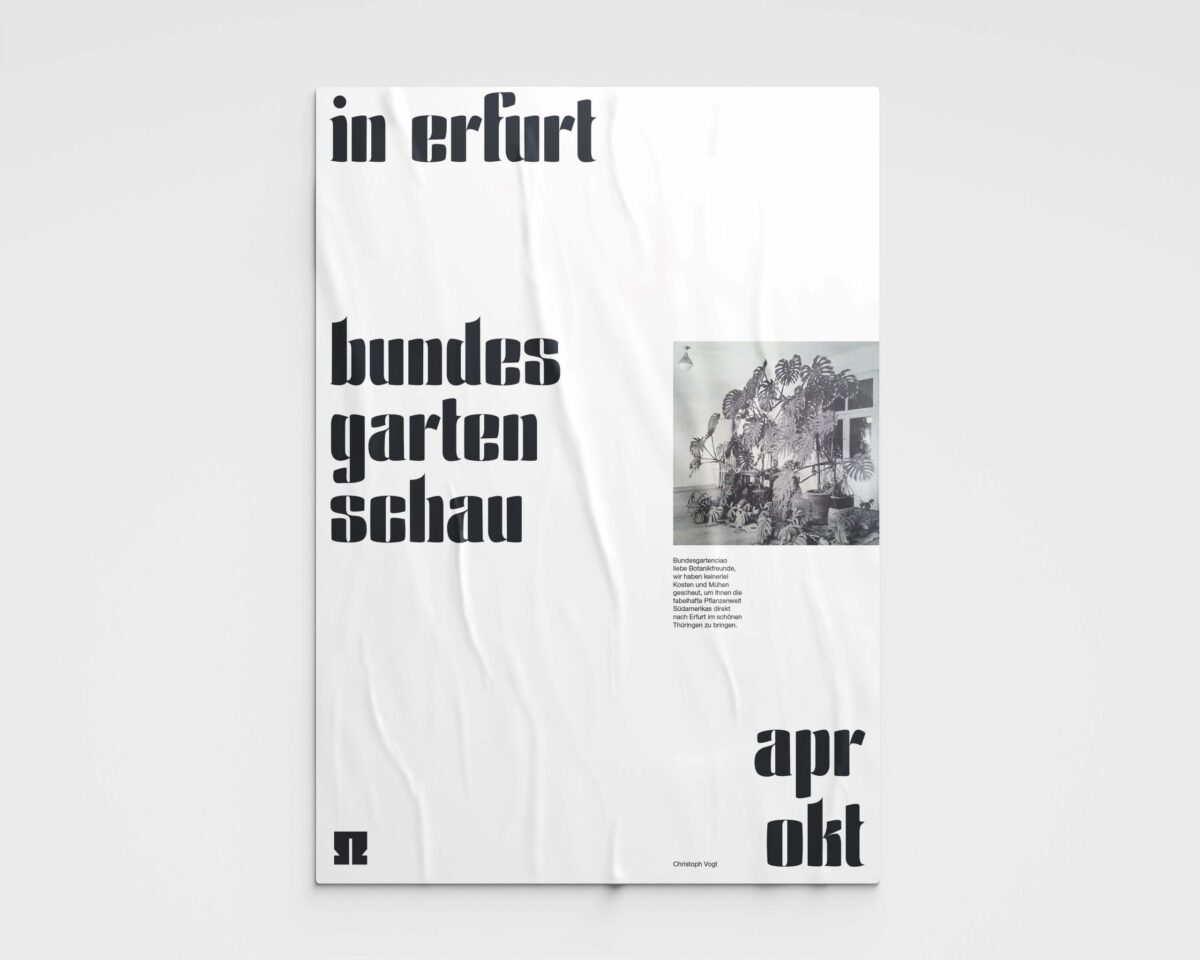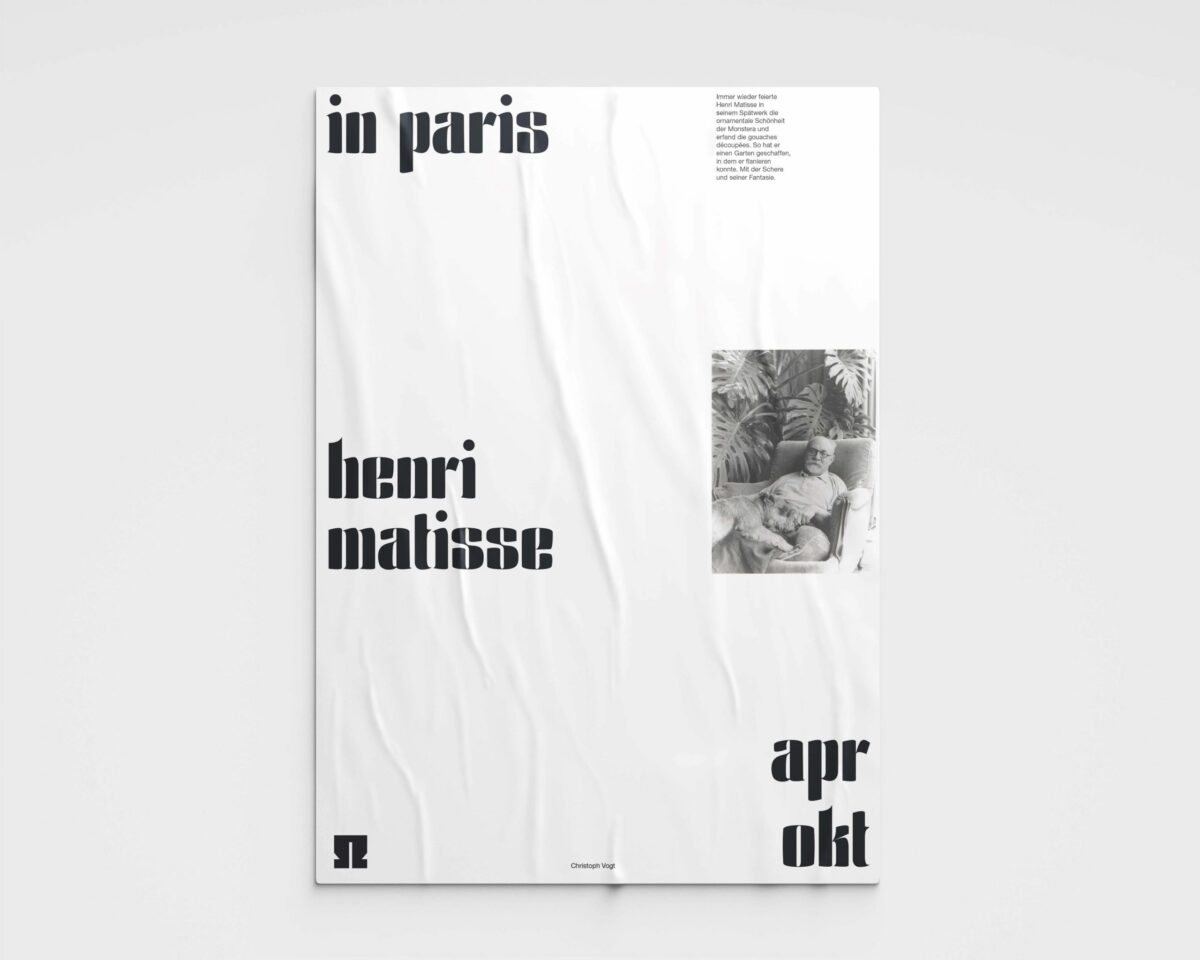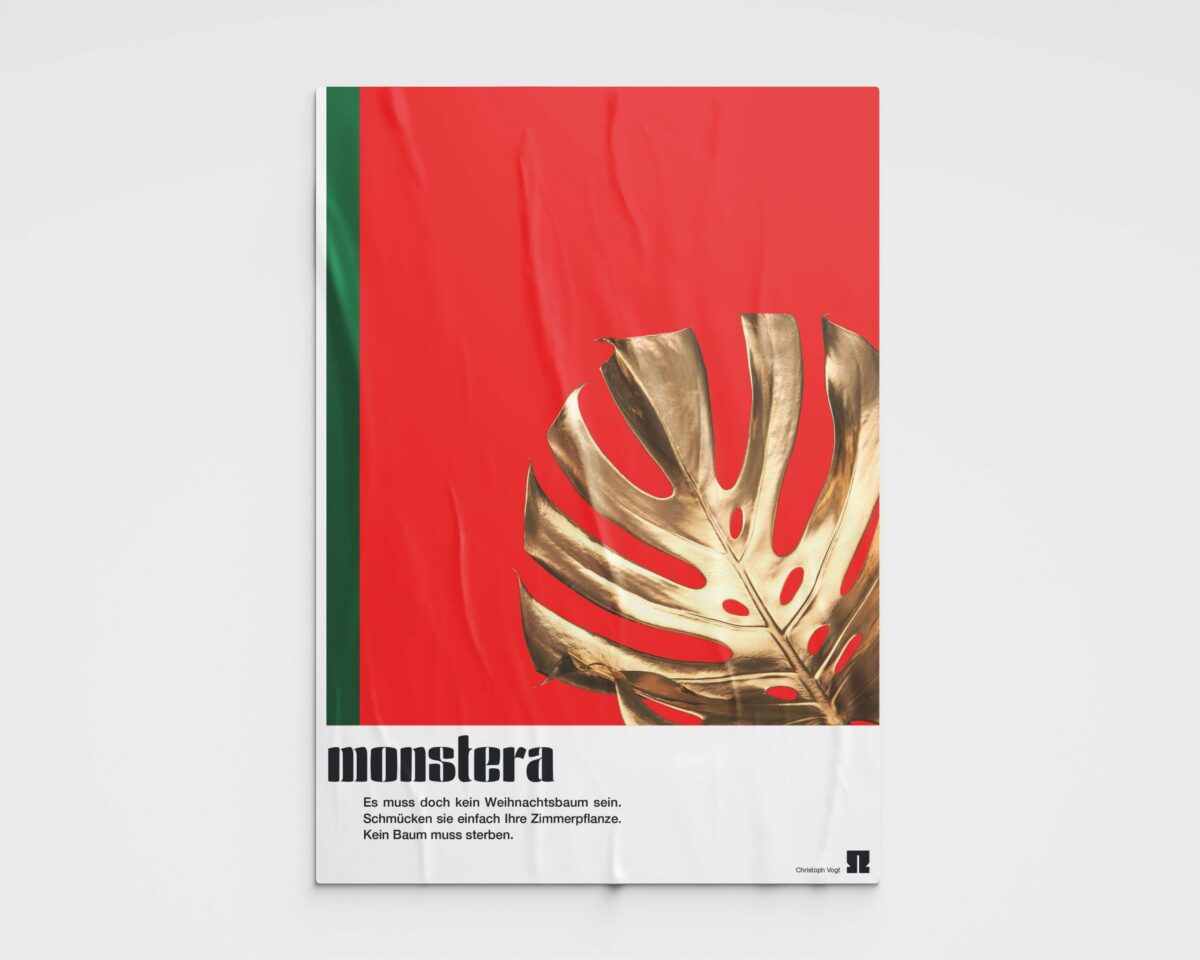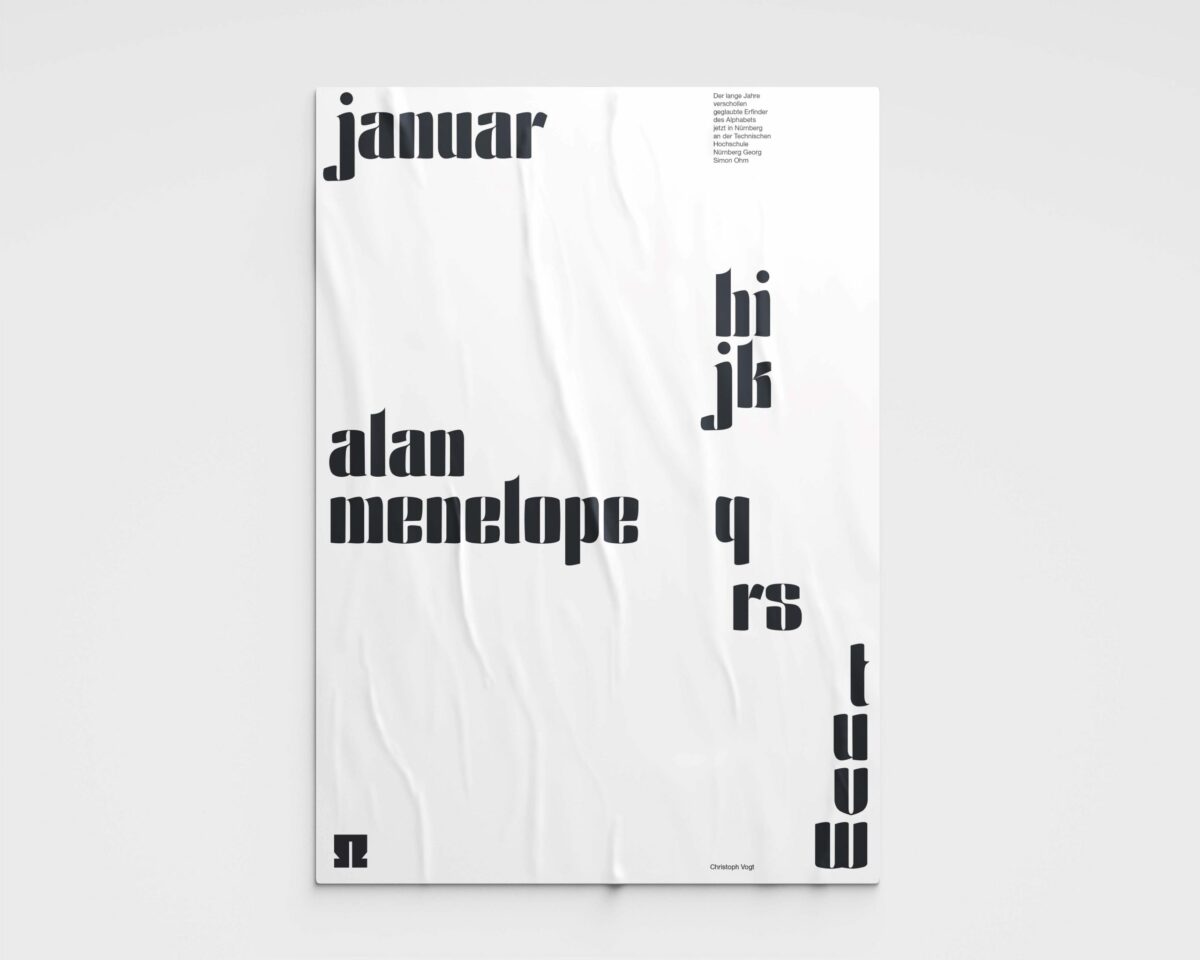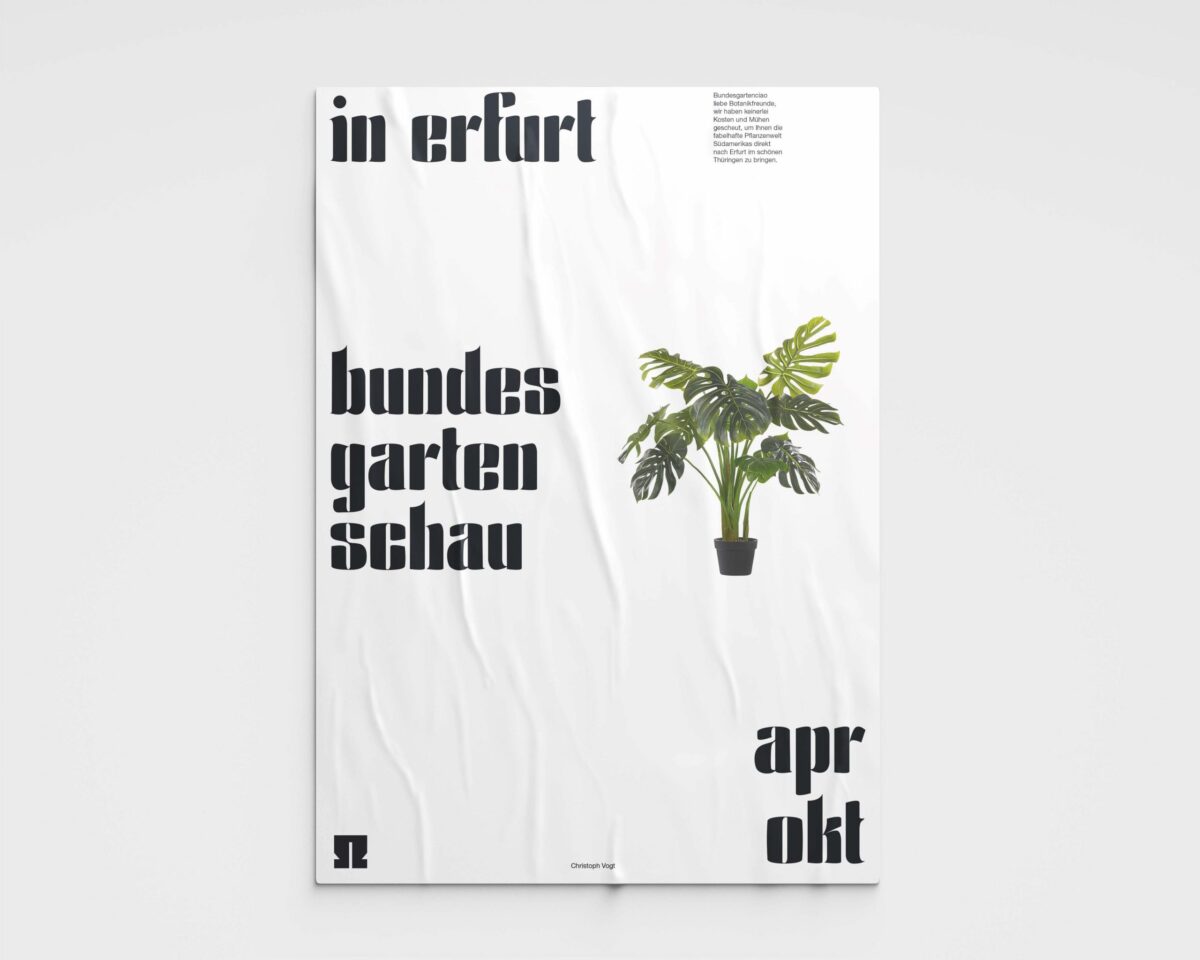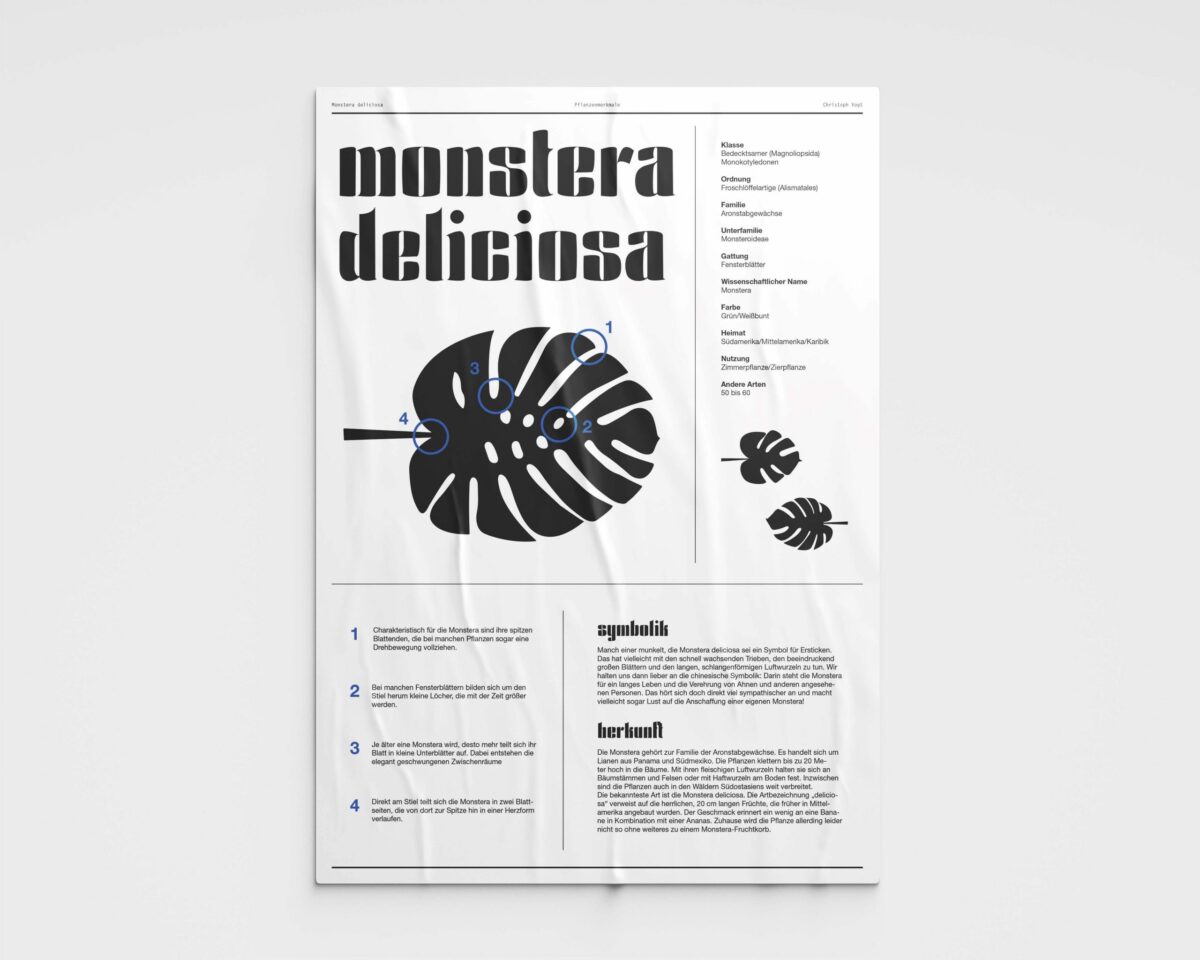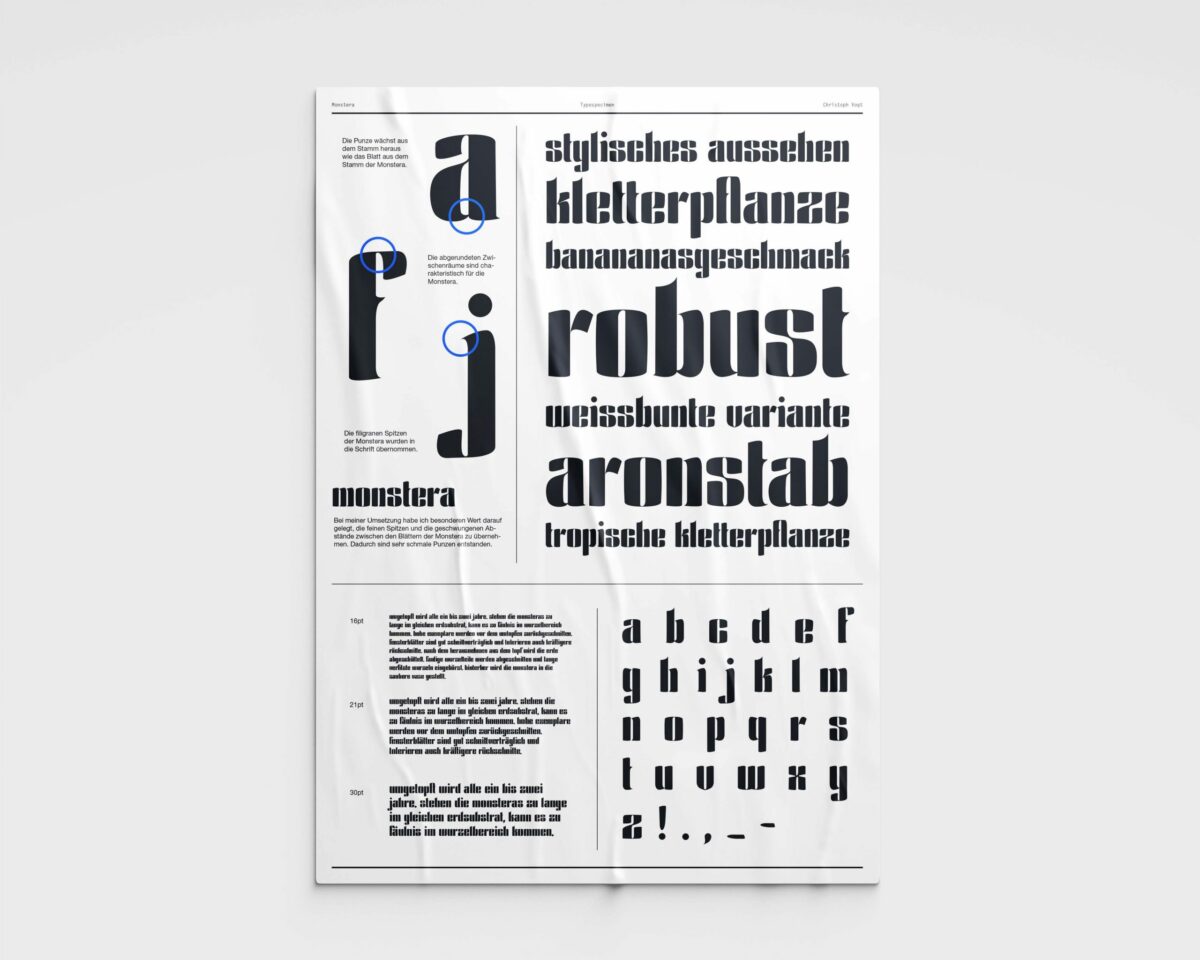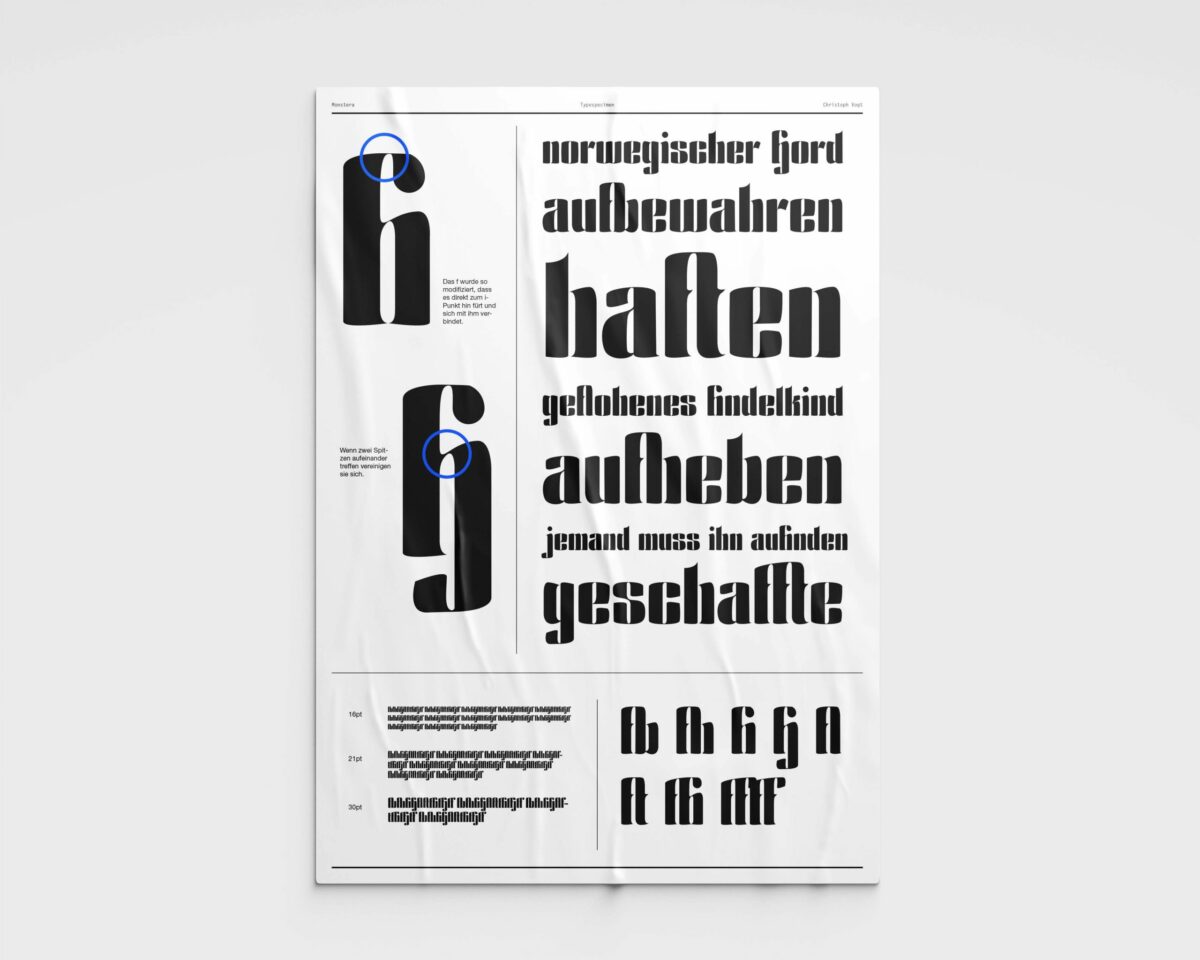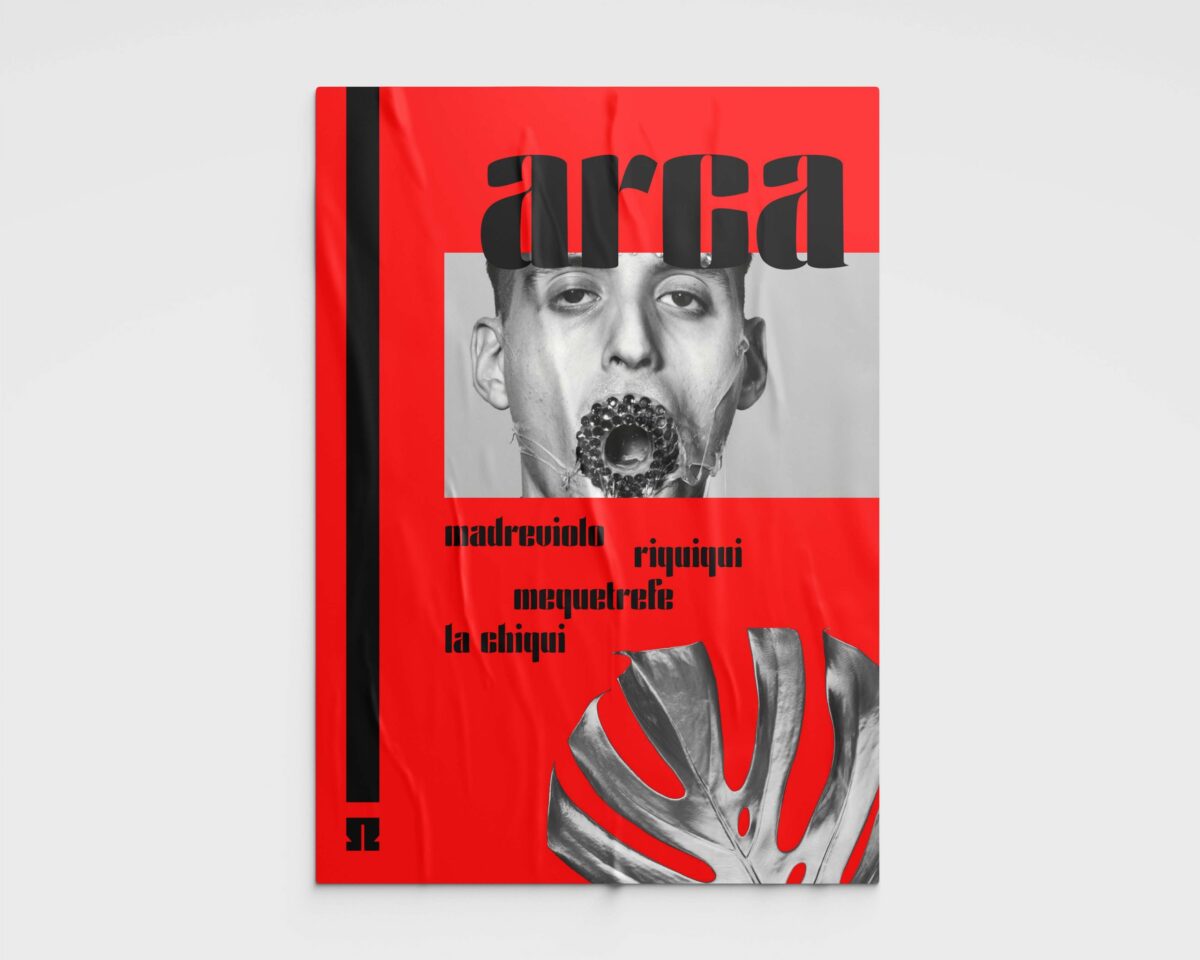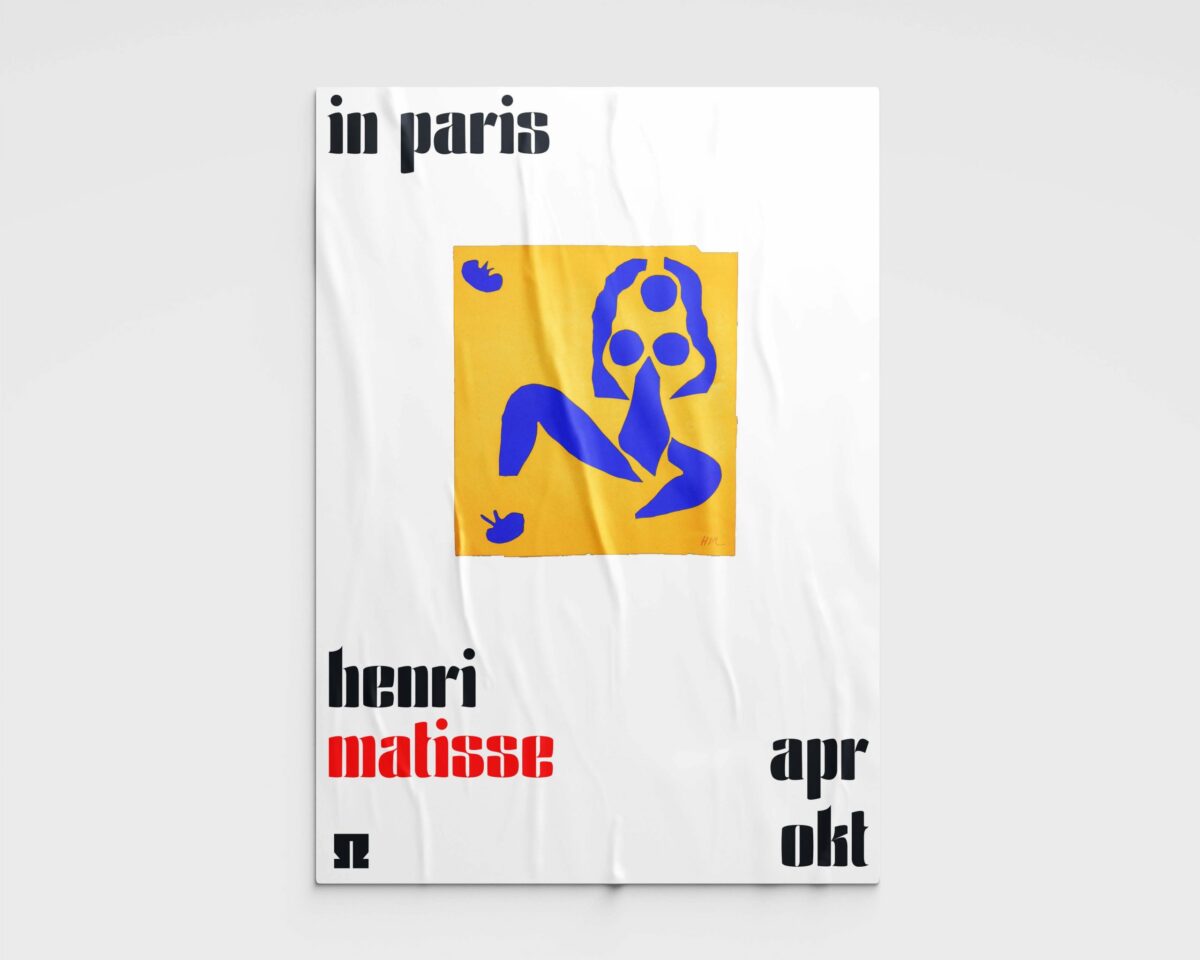
Monstera Font
von Christoph Vogt
Bundesgartenciao liebe Botanikfreunde,
ich habe eine Schrift kreiert und mich dabei vom Blatt der Monstera inspirieren lassen. Ihr seht hier ein paar Anwendungsplakate.